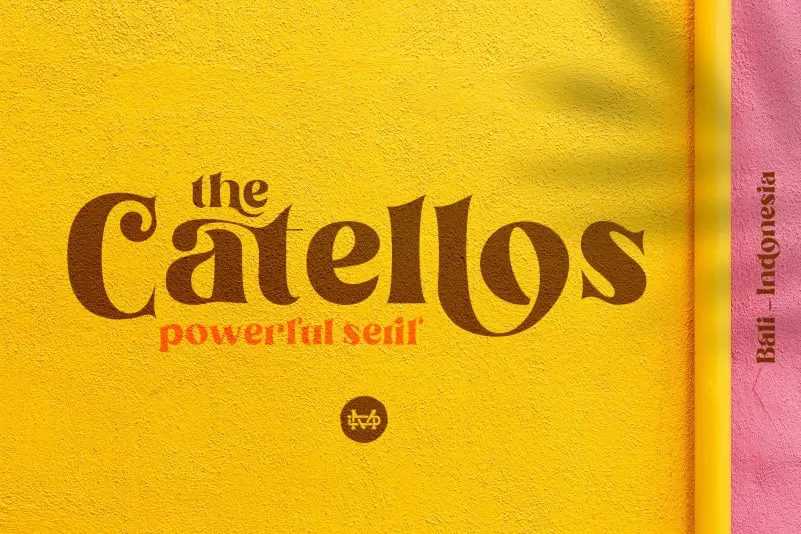
Catellos Serif Font – Download Grátis
Catellos Serif Font é uma família serif que traz duas variantes de negrito, médio e bold, com alternativas e ligaturas abundantes. Esta fonte foi projetada para um uso variado em diferentes ambientes, desde criação de marcas e embalagens de produtos até cartas pessoais e materiais promocionais como etiquetas e logotipos. Suas características sofisticadas e elegantes tornam-a uma escolha perfeita para qualquer projeto que valorize um design clássico e sofisticado. Sempre uma ótima opção para quem deseja dar um toque refinado em seus materiais gráficos, Catellos Serif Font é uma fonte de serif ideal para designers e criadores de conteúdo no Brasil e em todo o mundo.